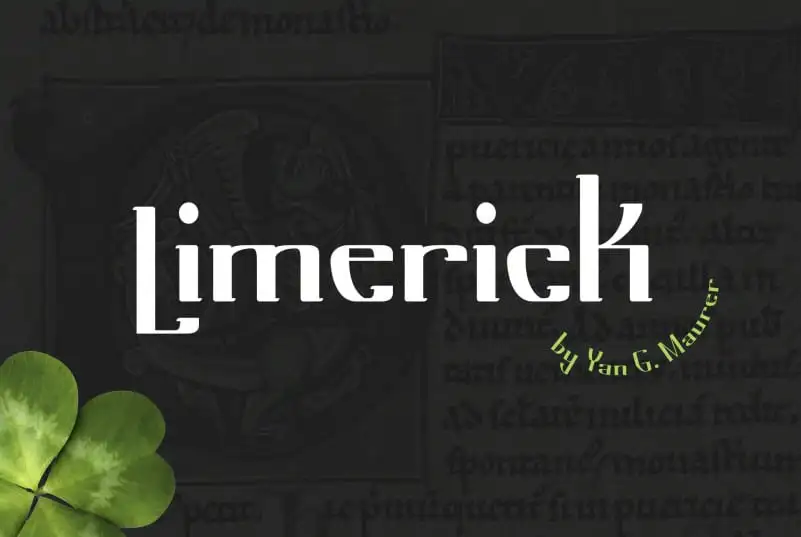
Limerick Serif Font – Download Grátis
A Limerick Serif Font é uma tipografia serif inspirada na Irlanda medieval. Com suas linhas retas combinadas com uma leve curvatura, essa fonte moderniza e torna-se atraente. É perfeitamente adequada para cabeçalhos de sites, logos, histórias em quadrinhos no Instagram ou marca de moda. Experimente letras maiúsculas para um visual limpo e elegante. Seja qual for o uso, essa fonte é uma escolha perfeita para aqueles buscando elementos gráficos modernos e atraentes. Não há dúvida de que Limerick será uma ótima adição à sua biblioteca de recursos gráficos.